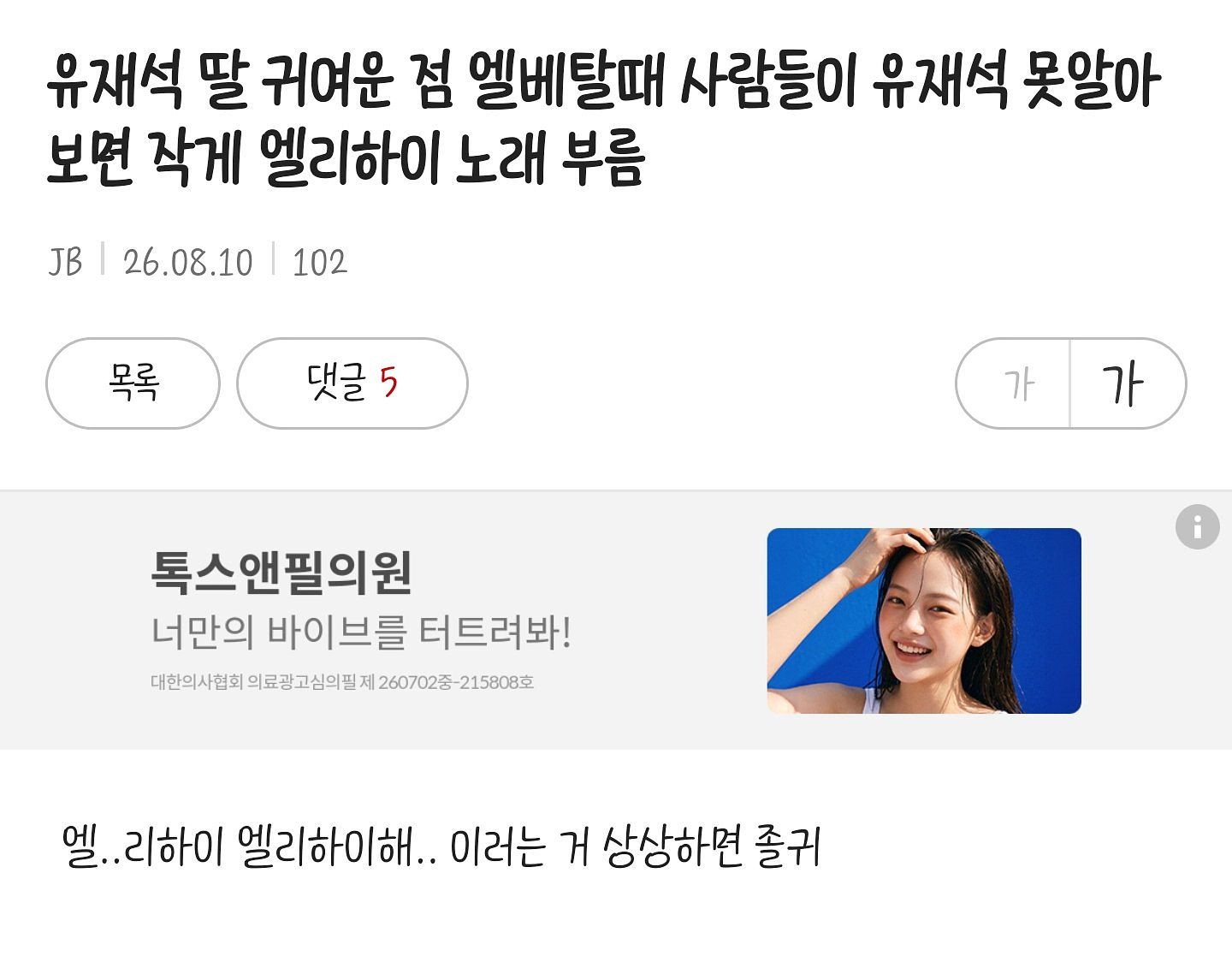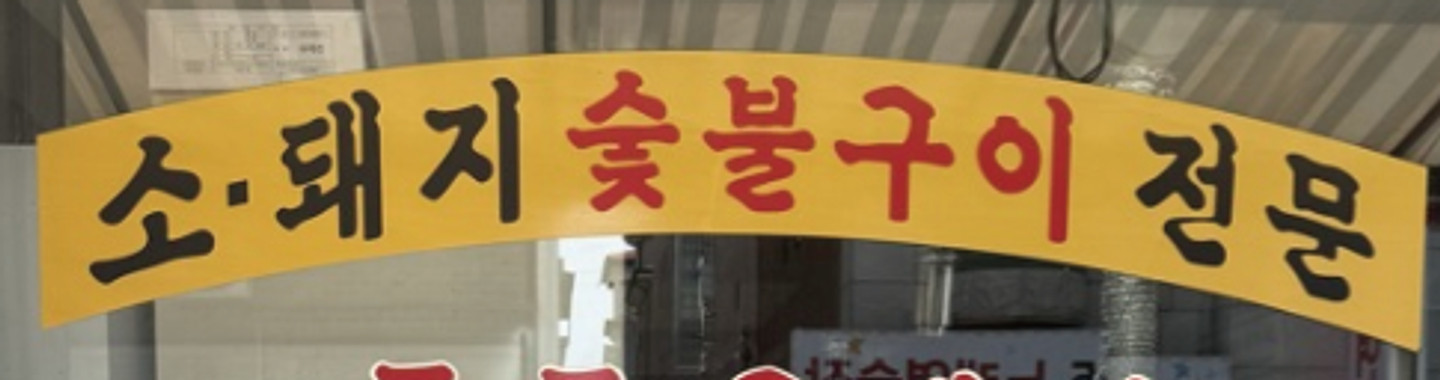
Choc
비슷한 폰트 2가지 찾았습니다: 하나는 Linotype의 Choc(https://www.myfonts.com/collections/choc-font-urw)이고 다른 하나는 Bitstream의 Staccato 555(https://www.myfonts.com/collections/staccato-555-font-bitstream)입니다. 캡처 속 "e"자가 좀 다르게 보이긴 하지만 굵기 차이 때문인 거 같습니다.